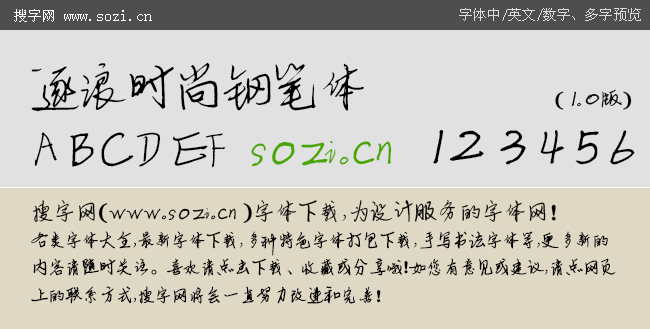
逐浪時(shí)尚鋼筆體
搜字網(wǎng)提供一款逐浪時(shí)尚鋼筆體中文書(shū)法字體下載,逐浪時(shí)尚鋼筆體是一款手寫(xiě)風(fēng)格的鋼筆書(shū)法字體,字體書(shū)寫(xiě)流暢,字形大方,整體效果十分出色,適合應(yīng)用于廣告設(shè)計(jì)、名片設(shè)計(jì)、包裝印刷、產(chǎn)品設(shè)計(jì)等應(yīng)用。